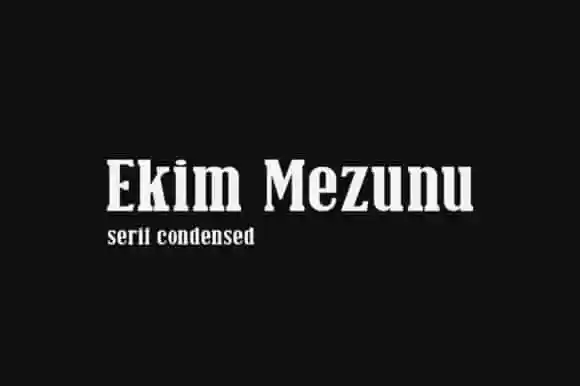
Ekim Mezunu Slab Serif Font
Introduzimos a fonte ‘Ekim Mezunu Slab Serif Font’, uma tipografia serifizada com contraste agudo para ambientes sofisticados e elegantes. Desenhada cuidadosamente por AmruID, esta font se destaca por suas detalhes finos e variedade abrangente. Ideal tanto para marcas contemporâneos quanto para grandes marcas de luxo, Ekim Mezunu Slab Serif é uma excelente escolha para impulsionar ainda mais sua identidade visual. Com seu design meticuloso e contraste vibrante, a font promete trazer seus projetos criativos ao próximo nível. Descubra a essência dessa nova adição à sua biblioteca de recursos gráficos.